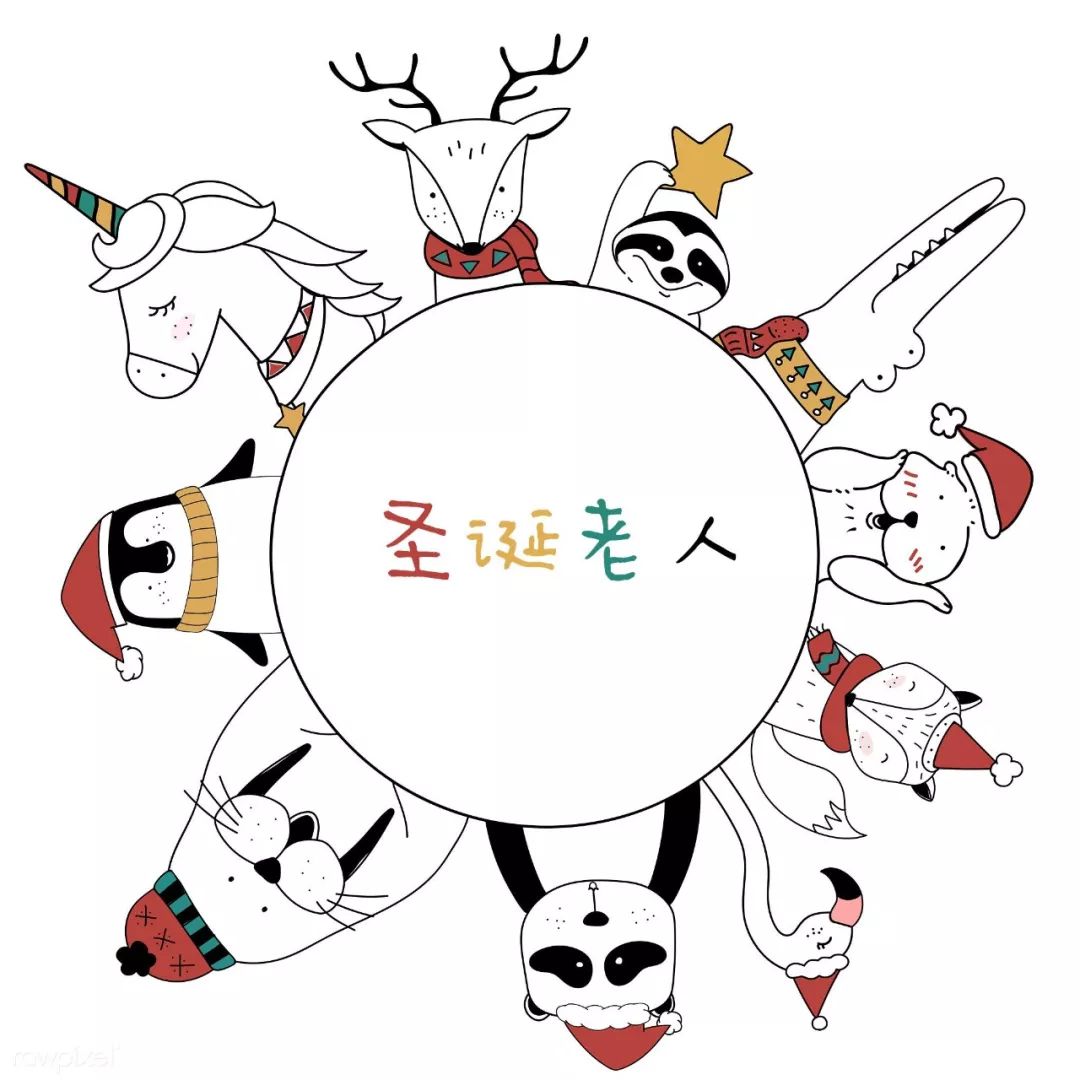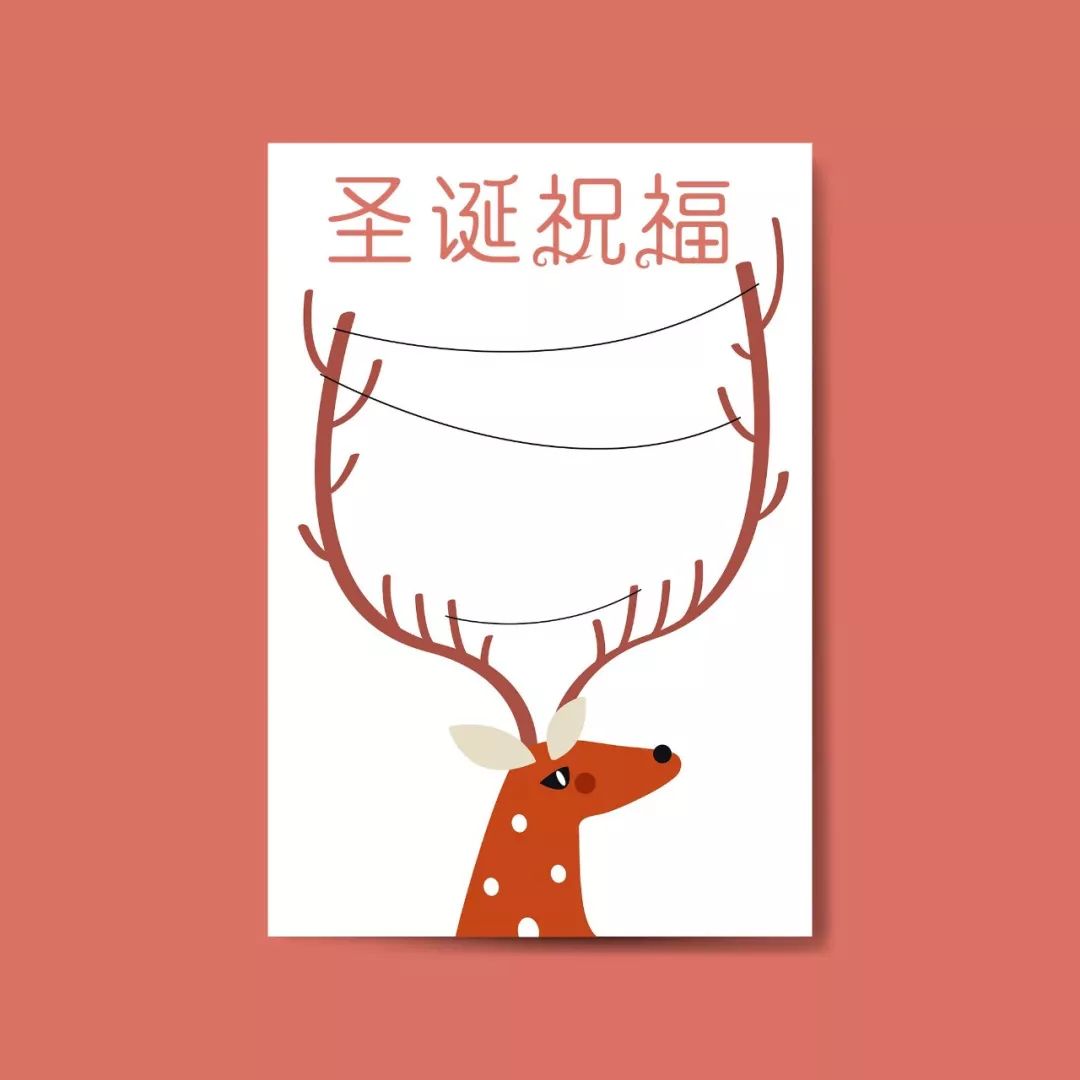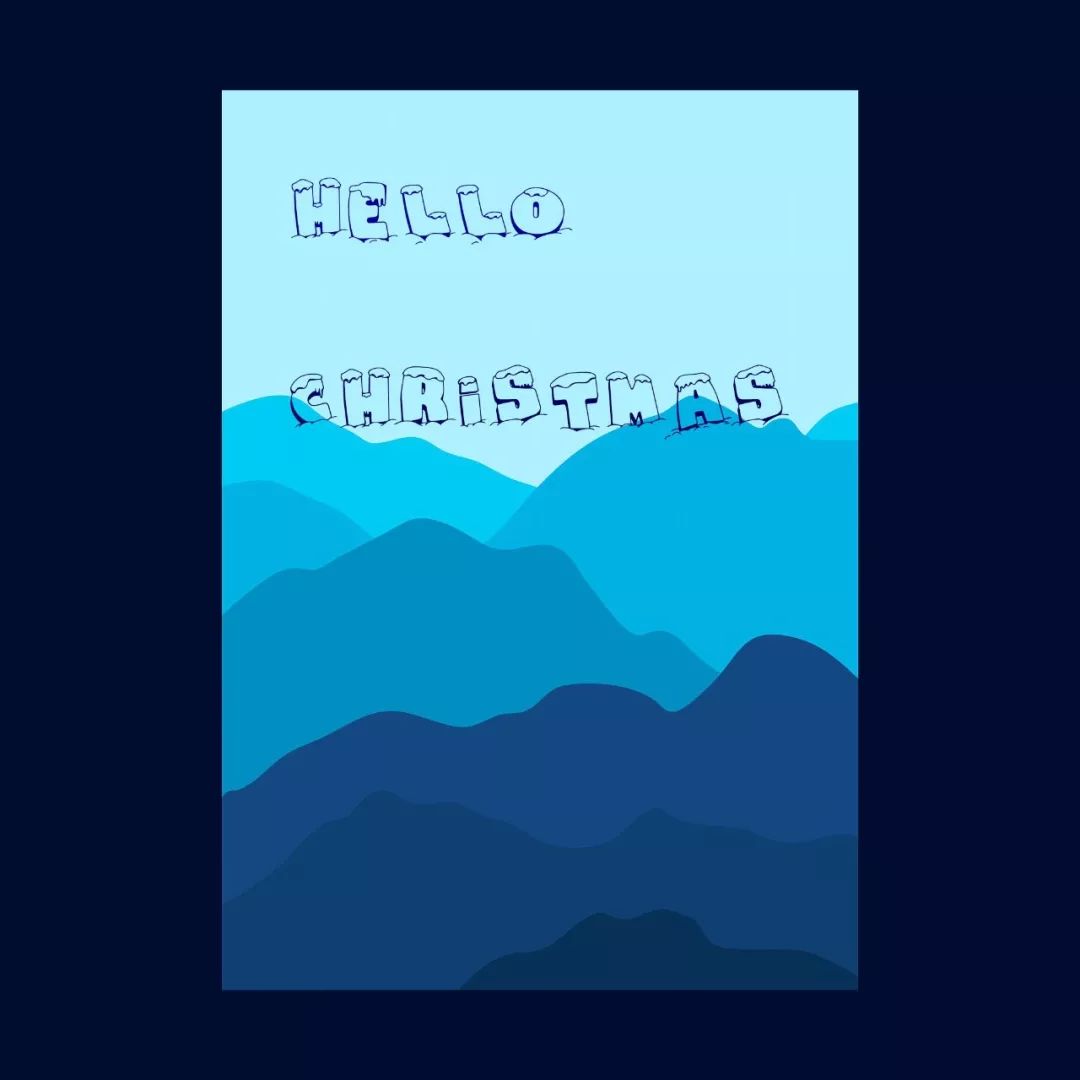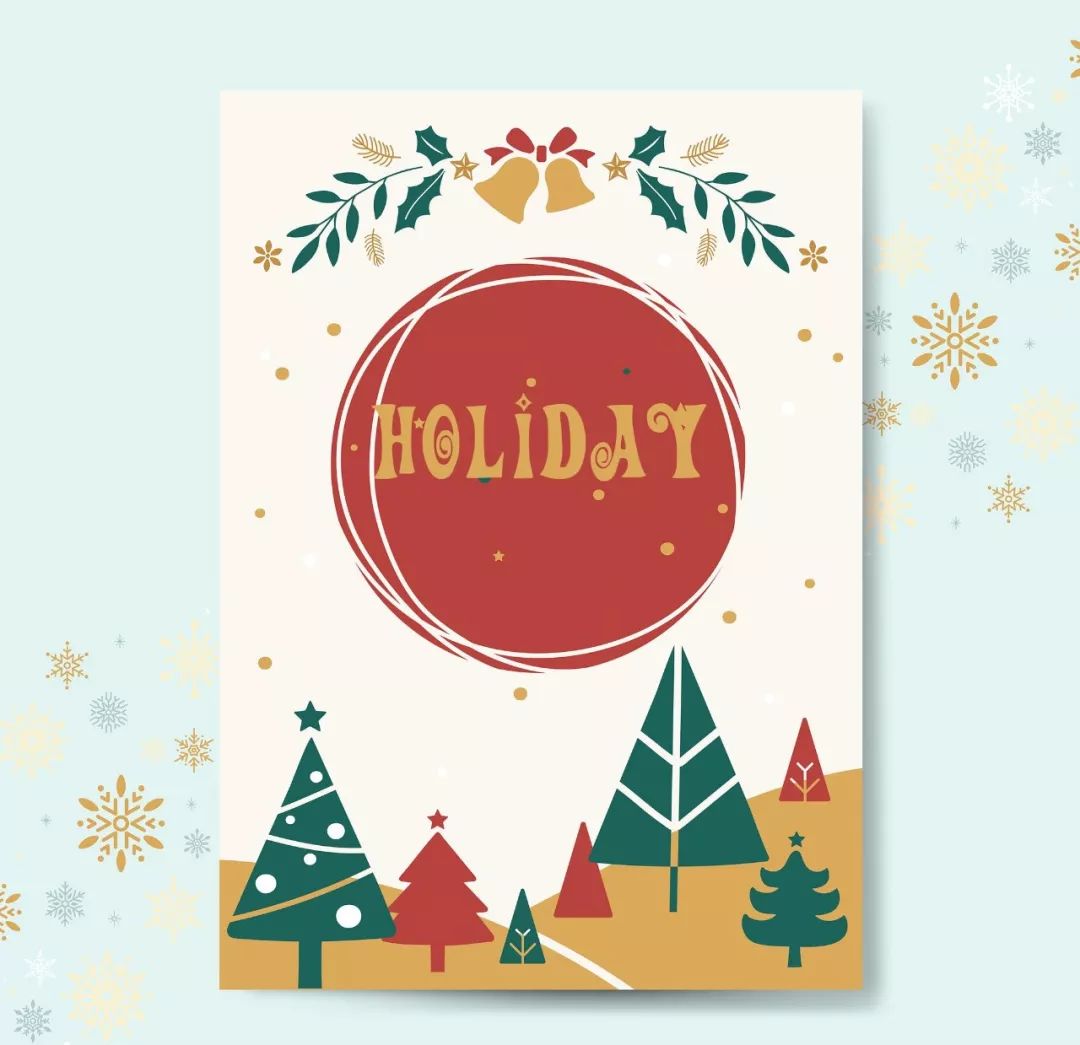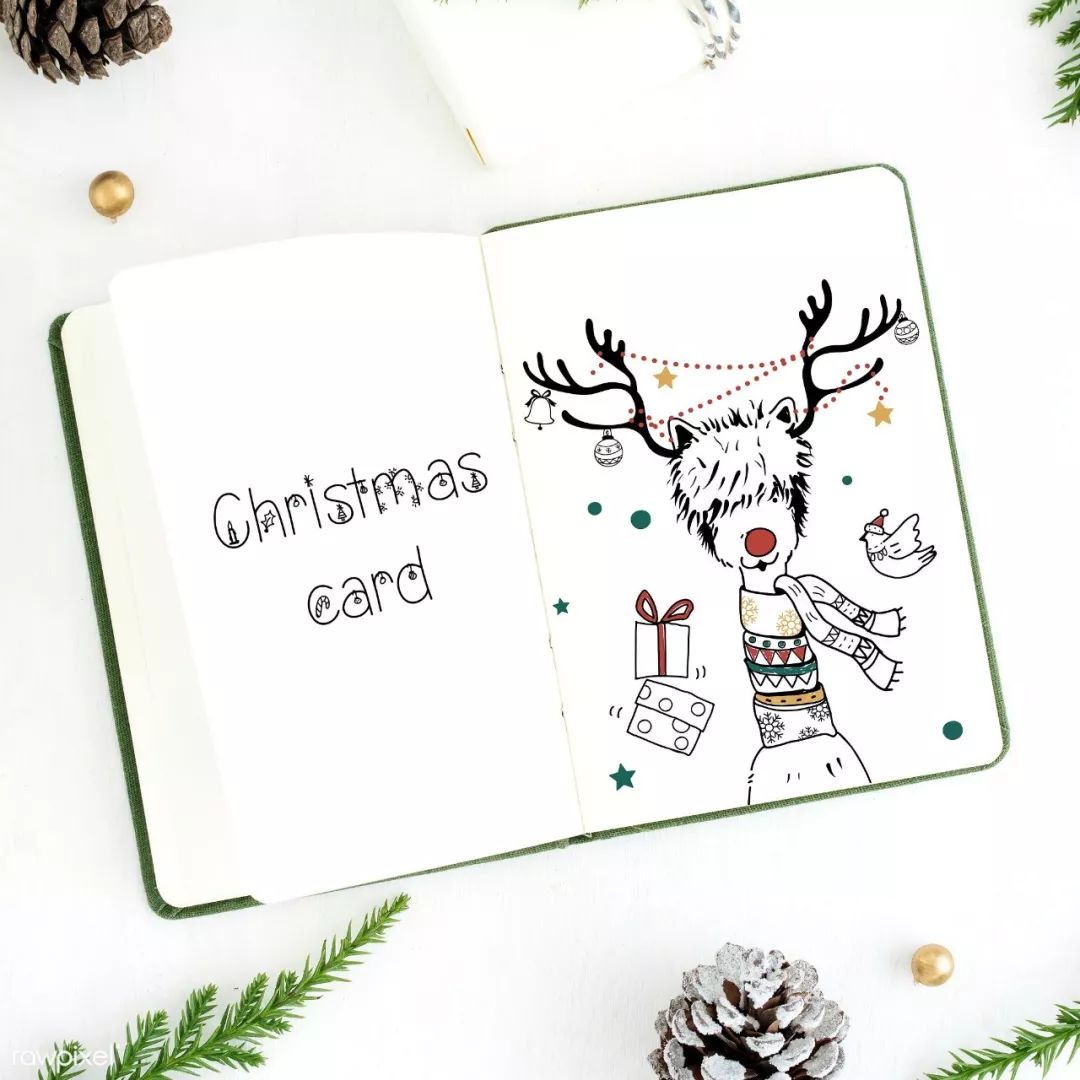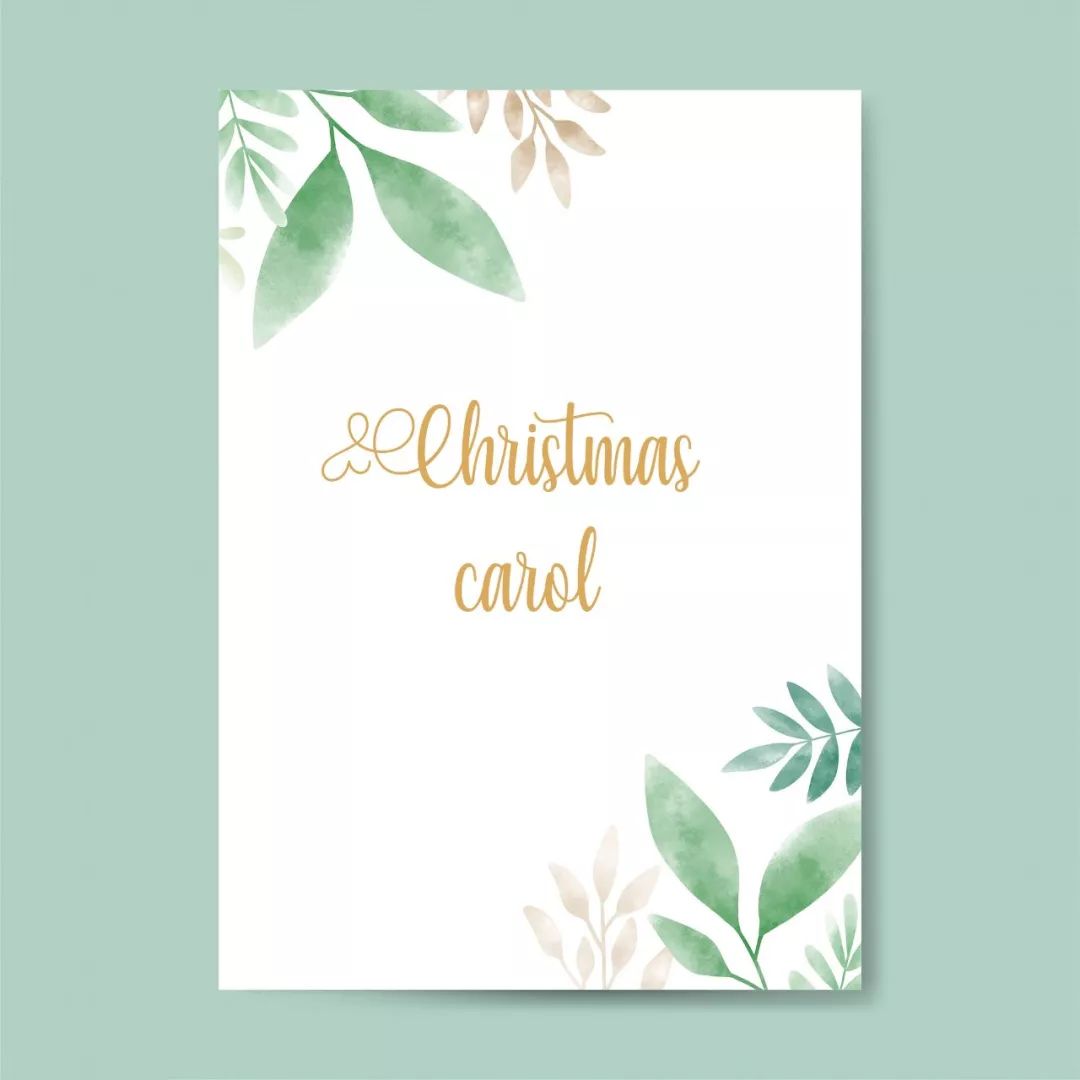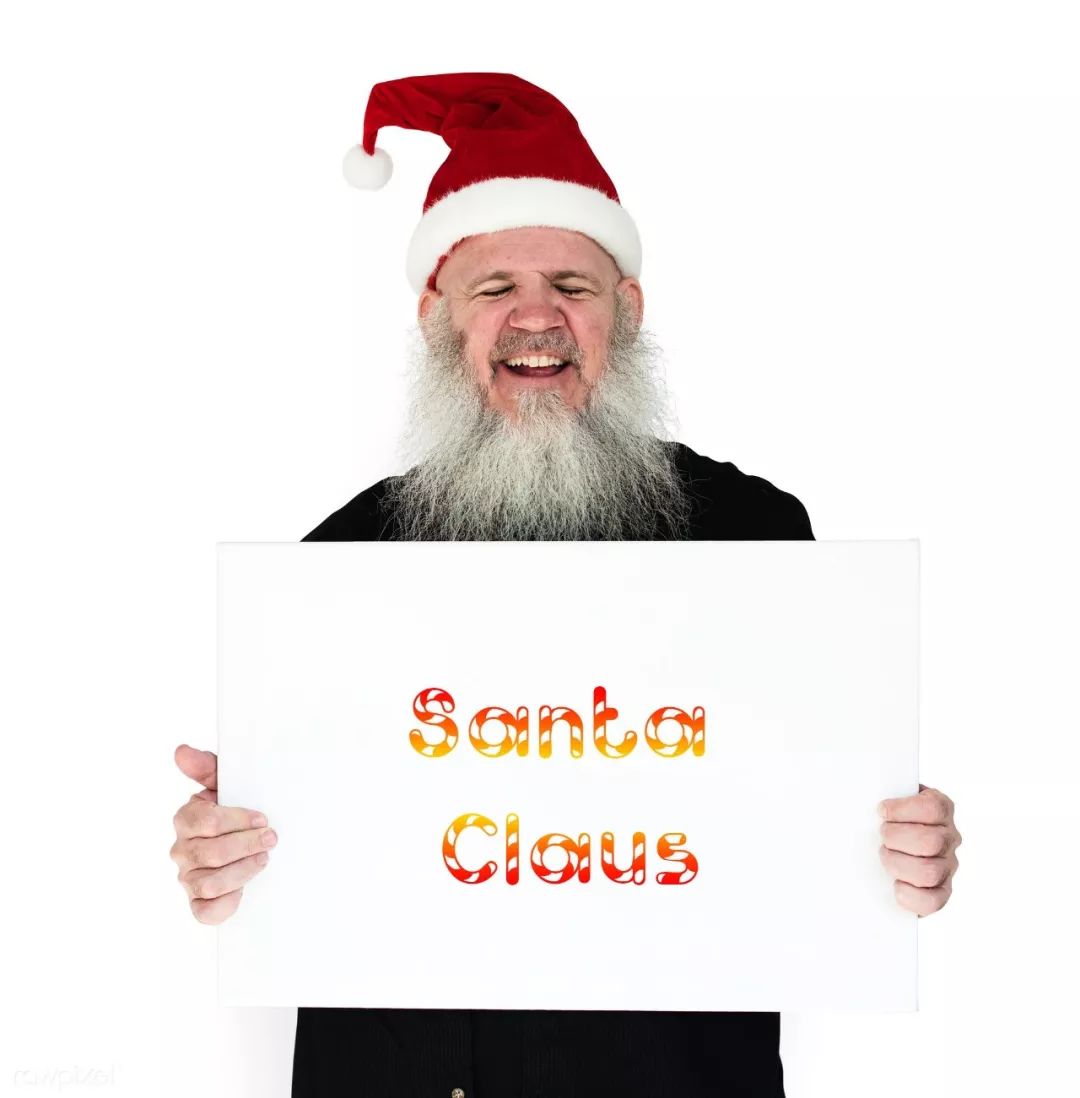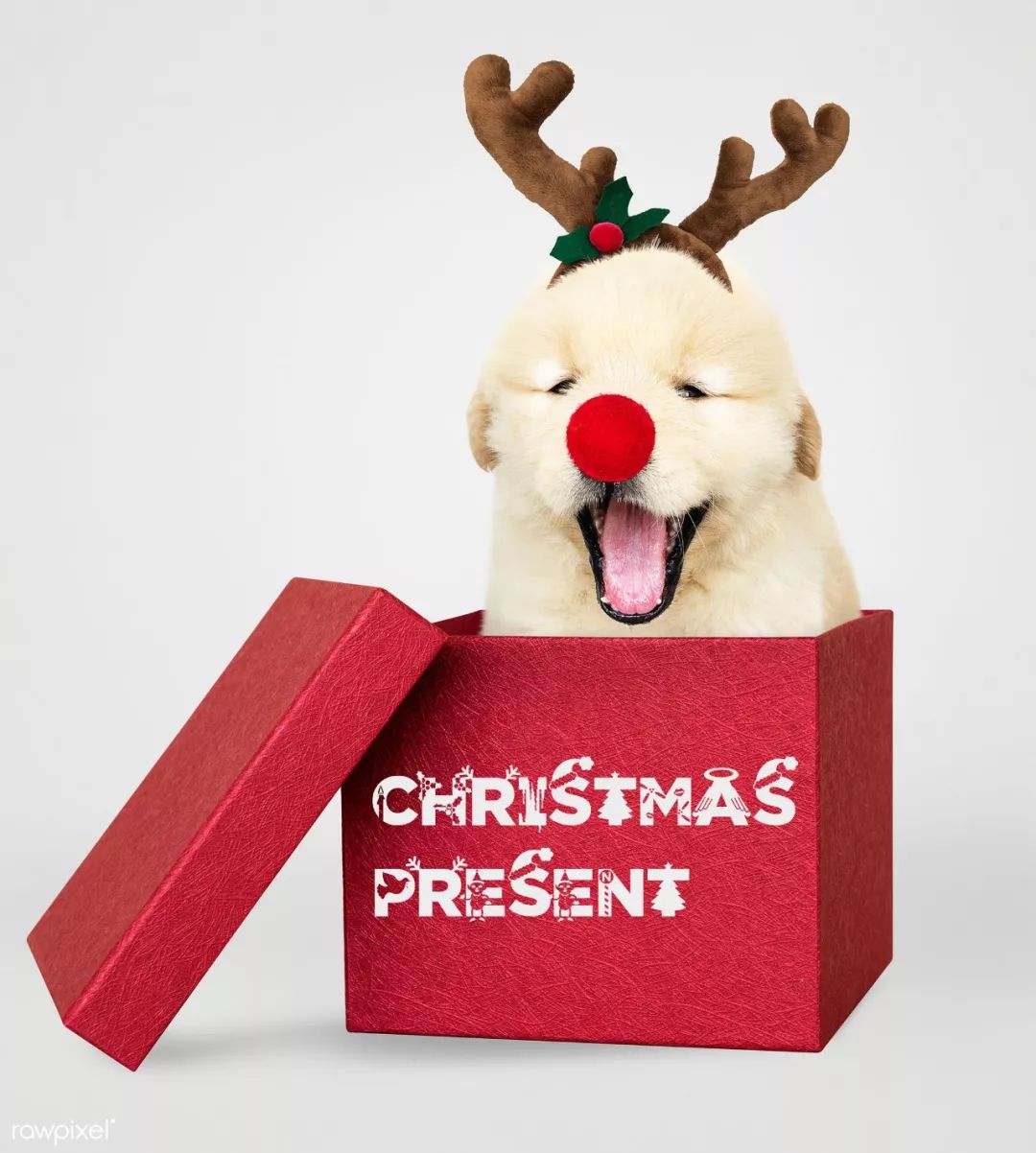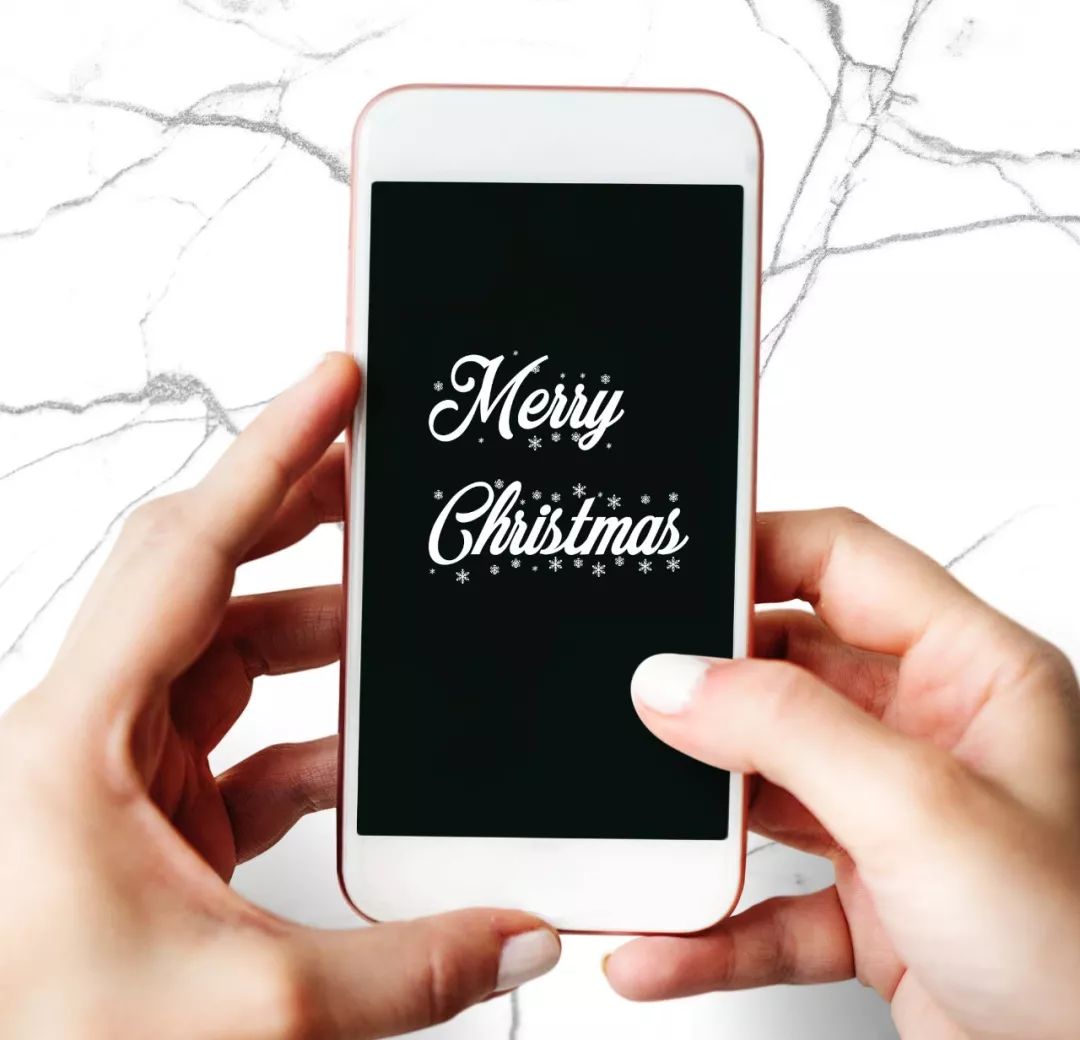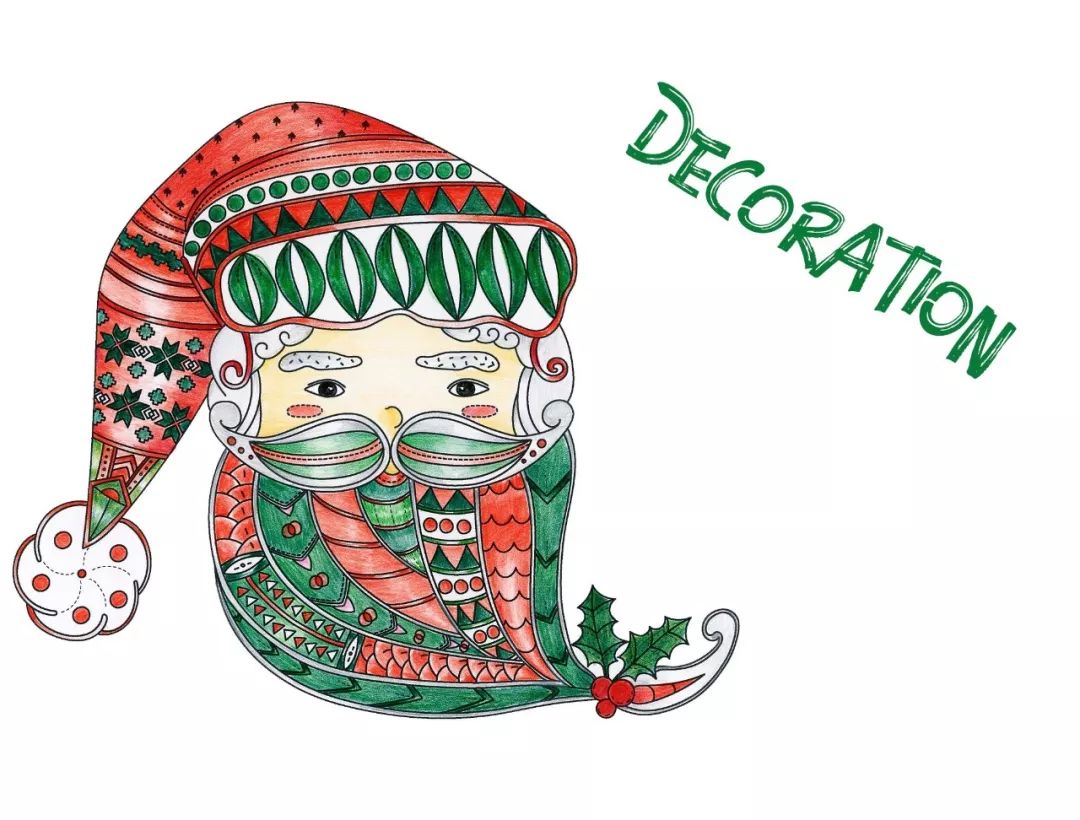
圣诞节字体、笔刷、纹理等素材分享
每次一到节日,设计师就关心两件事,一个是找素材,一个是找教程,放假?不存在的,少掉点头发,就阿弥陀佛了~
不过这都不是我今天要说的重点,那我在干嘛?当然是搞大事情≡≡≡
如果你喜欢“圣诞节”
虽然是个歪果节,但我们在设计的时候,也不能老是Merry Christmas的吧!所谓西学东渐,就是要吸取圣诞节的精髓,有哪些字体适合呢?
如果你喜欢卡通可爱
接下来就是字由新上的西文了,正宗飘洋过海来的味道,敲可耐滴~
如果你喜欢优雅手写
只要是节日,怎么能少得了花花的手写体,虽然我分不太出来谁是谁,但就是看哪个都不舍得放弃,自带淑女气质~
如果你喜欢创意搞怪
有创意的字体,永远都能超出你的想象,那么我们开始吧~